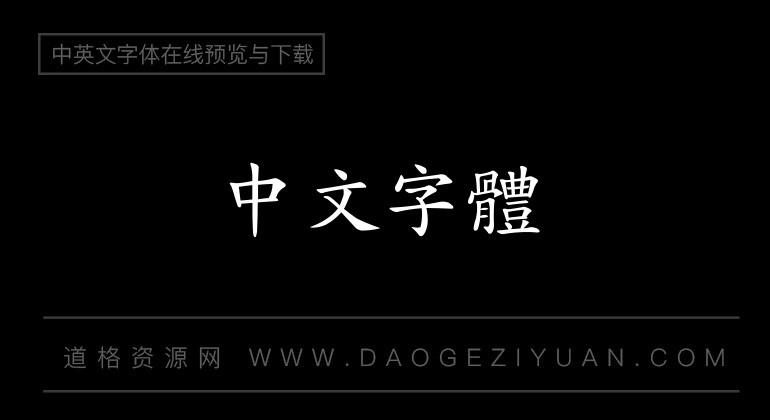
汉鼎繁楷体
汉鼎繁楷体是一款由汉鼎设计团队设计的繁体字体,它的特点是拥有浓郁的中国风,笔画优雅,字形端庄大方,更有英文字体搭配,可以满足不同风格的需求。它的字形特点是拥有较长的横笔画和较短的竖笔画,字体粗细恰到好处,笔画更加流畅,更具有艺术性。
汉鼎繁楷体是一款非常不错的手写艺术字体,具有很好的视觉感,适合于文化类的宣传设计、商业类品牌的广告和产品包装设计以及个性化文字排版等较多场景。